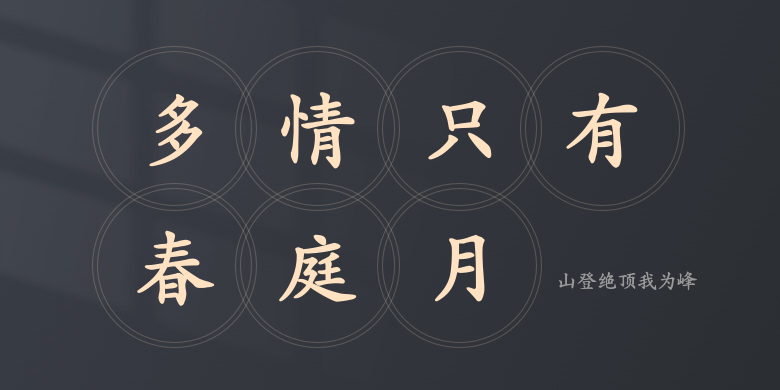
山登绝顶我为峰
山登绝顶我为峰,这款字体结构工整、笔画清晰,兼顾美观与易读性,适用于标题、正文、海报、包装、LOGO 等多种场景。字形优雅稳定,风格百搭耐看,适配日常排版与创意设计,让文字呈现更舒适、更具质感。山登绝顶我为峰一笔一画,皆是细节,以均衡的比例、流畅的线条打造舒适视觉体验,字形端正大气,风格简约现代。无论是商业设计、品牌宣传还是日常排版,都能轻松驾驭,让文字更有格调与力量。山登绝顶我为峰字体下载。